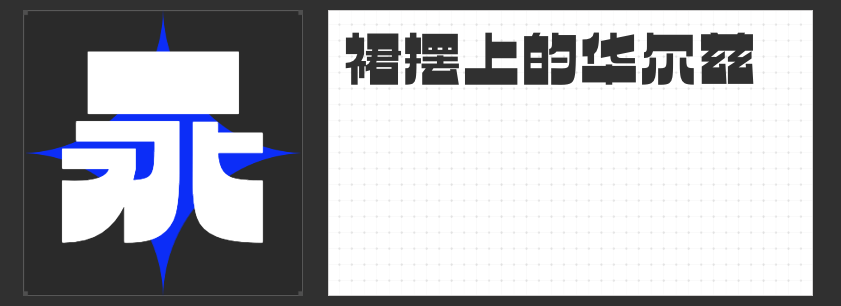
创意无限,设计首选:四款杰出字库字体推荐
在设计的世界里,字体不仅仅是文字的载体,更是情感与风格的传递者。今天,为大家推荐四款专为设计而生的创意字体,它们各具特色,能在瞬间提升作品的视觉冲击力与艺术感。
一、励字暴风简 超级黑:现代文艺的硬派演绎
作为现代创意型黑体的代表,励字暴风简 超级黑以其厚重的字型与开放的姿态,打破了传统黑体的界限。笔画粗细不均,横竖呈梯形分布,不仅保留了现代黑体的骨架,更在撇、捺、点上巧妙融入梯形元素,展现出一种不规则而又不失和谐的美感。这种风格偏硬的字体,无疑是现代文艺设计的绝佳选择。
二、励字逆反差圆舞简 超级黑:方圆之间的平衡艺术
逆反差圆舞简 超级黑,一款集方正与柔美于一身的字体。它在逆反差直线版的基础上,巧妙地将部分笔画转化为饱满的弧线,营造出一种既稳定又灵动的视觉效果。中宫宽敞,重心稳固,笔画对称,使得这款字体在保持强烈视觉对比的同时,又不失和谐与优雅,适用于多种设计场景。
三、励字铁拳简 超级黑:力量与美学的完美融合
励字铁拳简 超级黑,一款以力量为名的创意黑体字。笔画粗壮,字面宽大,块面感饱满,折角圆润而不失力度,仿佛每一笔都在诉说着不屈与坚韧。这种字体犹如铁拳出击,直击人心,适合需要强烈视觉冲击力的设计项目,如电影海报、运动品牌宣传等。
四、高手字斋哥特体Pro:复古暗黑的视觉盛宴
高手字斋哥特体Pro,一款超粗哥特中文字体,以其复古而暗黑的风格,成为设计界的独特存在。这款字体不仅保留了哥特字体的经典特征,如细长的笔画、尖锐的顶端,更在粗细对比上做到了极致,营造出一种神秘而深邃的氛围,适合用于恐怖电影海报、暗黑风格品牌标识等。